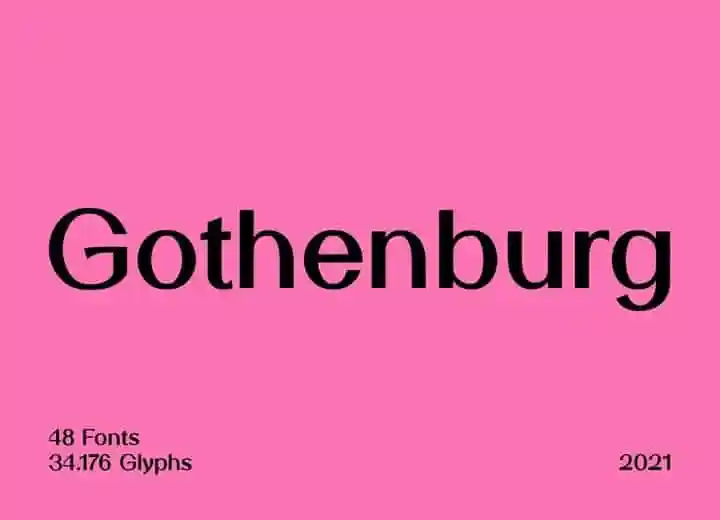
A SK Gothenburg Sans Serif é uma fonte moderna inspirada no entreligamento entre a estrutura histórica da cidade portuguesa de Gothenburg e sua vida contemporânea vibrante. Desenvolvida por Salih Kizilkaya, essa fonte elegante combina elementos typográficos essenciais para quem busca um visual clean que combine conforto de leitura com uma aparência contemporânea. Suas linhas retas e minimalistas criam um tom suave que se adapta perfeitamente a diversas aplicações, seja no design editorial, na web ou em projetos gráficos digitais. Seja para criar logotipos distintivos ou texturas de alto padrão, a SK Gothenburg Sans Serif é uma escolha inteligente para quem busca uma fonte moderna e sofisticada que mantém o charme do passado enquanto se adaptando ao futuro.